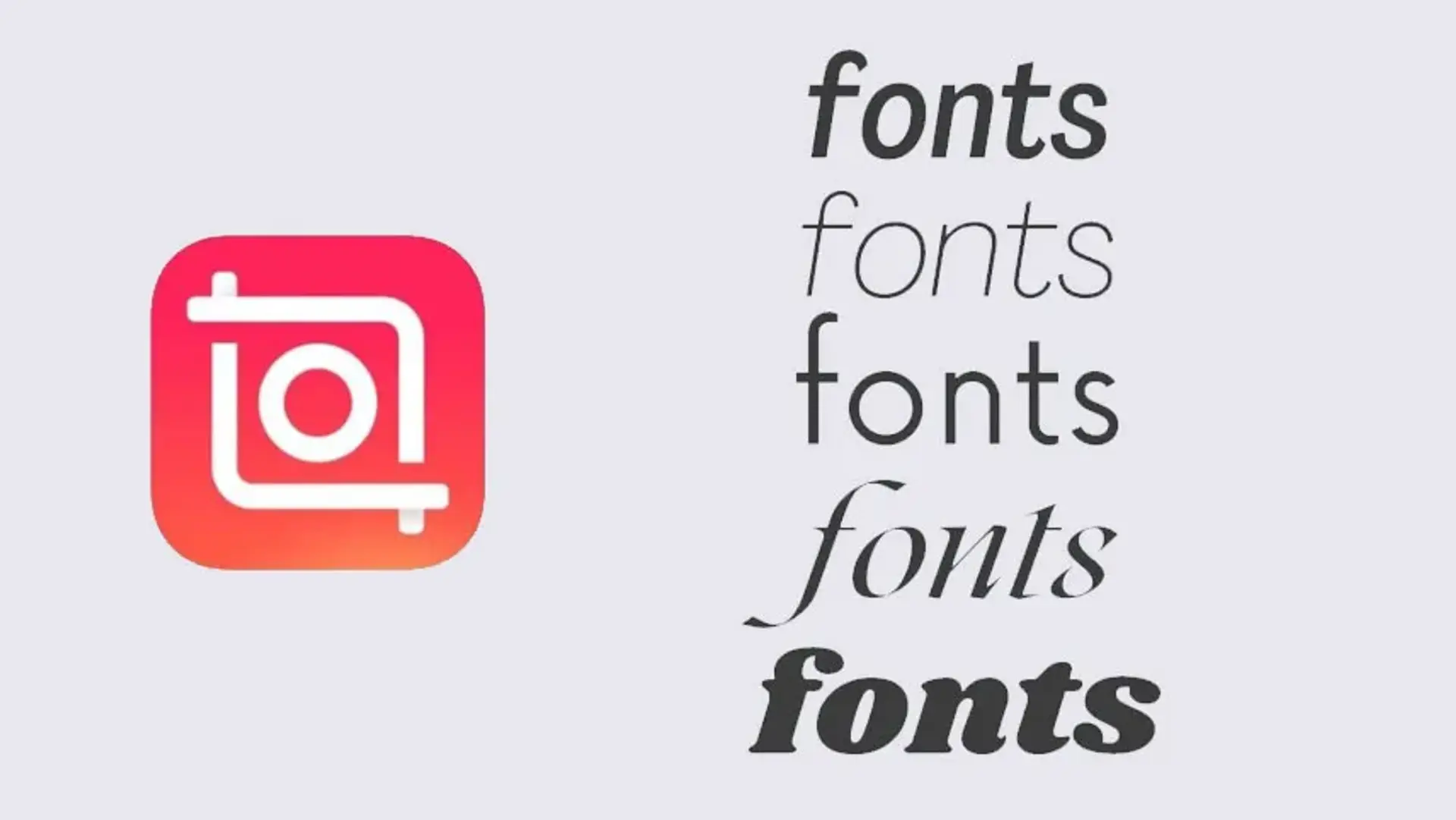
اینشات یکی از محبوبترین برنامهها برای ویرایش ویدیو و تصویر در گوشی محسوب میشود. یکی از امکانات قابل توجه اینشات، قابلیت نوشتن روی تصاویر و ویدیوها است که به کاربران این امکان را میدهد تا جلوه تازهای به محتوای خود بدهند. با این حال، فونتهای پیشفرض اینشات ممکن است تنوع کافی نداشته باشند و مهمتر از همه با زبان فارسی به طور کامل سازگار نباشند. خوشبختانه در اینشات میتوانیم با اضافه کردن فونتهای دلخواه، این مشکل را حل کرده و از هر فونتی که دوست داریم استفاده کنیم. در این مطلب میخواهیم با نحوه انجام این کار آشنا شویم. در این راهنمای کامل، ما علاوه بر معرفی جدیدترین روشهای نصب فونت، دقیقا نحوه رفع تمام خطاهای احتمالی را بر اساس تجربه عملی توضیح دادهایم. پس در ادامه با آموزش اضافه كردن فونت به اینشات در ایفون و اندروید، همراه پلازا باشید.
آموزش اضافه کردن فونت دلخواه به برنامه اینشات
استفاده از فونت جدید نه تنها متن را متمایز میکند، بلکه میتواند زیباتر هم به نظر برسد. برای مثال، اگر ویدیوی شما دارای تم قدیمی است، میتوانید یک فونت با سبک قدیمی مانند فونت ماشین تحریر را نصب و استفاده کنید. یک فونت منحصر به فرد خوب باعث میشود ویدیوی شما جذاب تر و حرفه ای تر به نظر برسد.
3. چرا باید از فونتهای جدید و سفارشی به جای فونتهای داخلی اینشات استفاده کنم؟
استفاده از فونتهای سفارشی به شما کمک میکند تا ویدیوتان منحصر به فرد، جذابتر و حرفهایتر به نظر برسد. اگر صرفا از فونتهای پیشفرض استفاده کنید، ویدیوی شما شبیه به ویدیوهای دیگری خواهد بود که با اینشات ویرایش شدهاند، زیرا همه کاربران فونتهای یکسانی دارند. یک فونت خوب میتواند با تم ویدیوی شما (مثلا تم قدیمی با فونت ماشین تحریر) مطابقت داشته باشد.